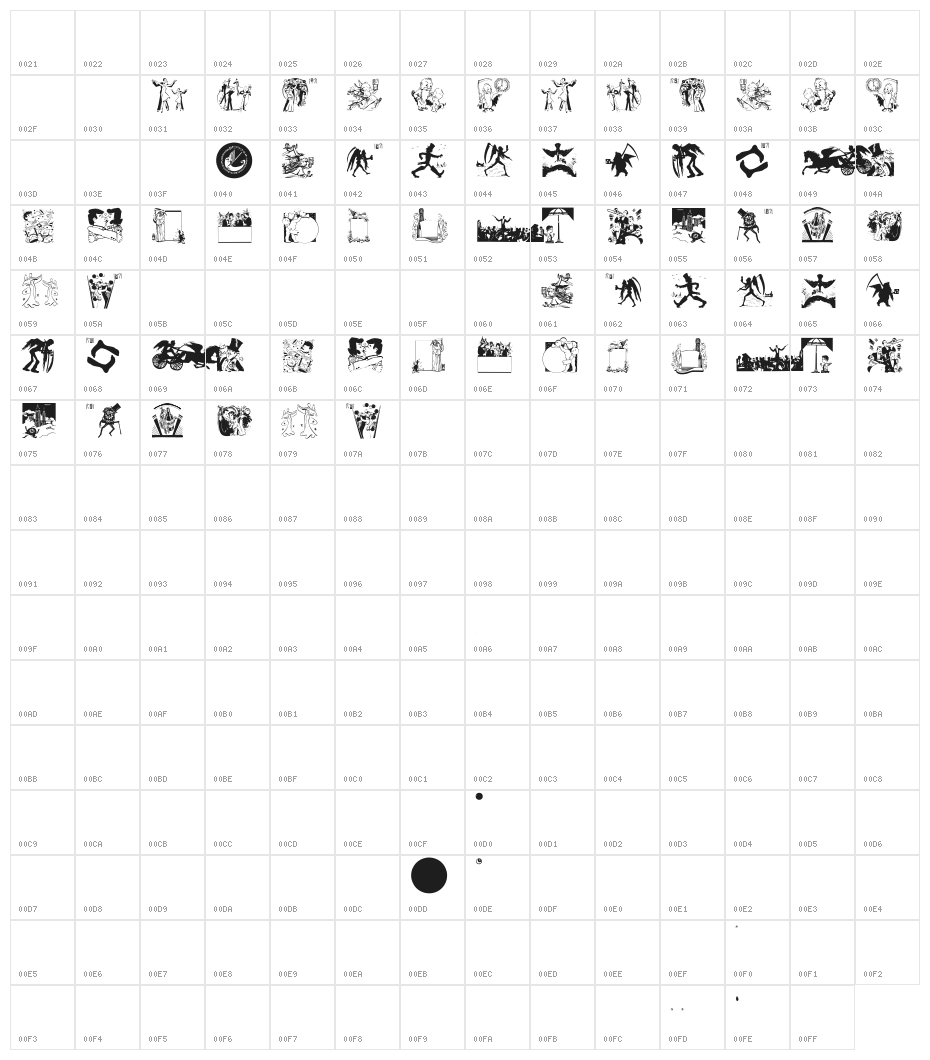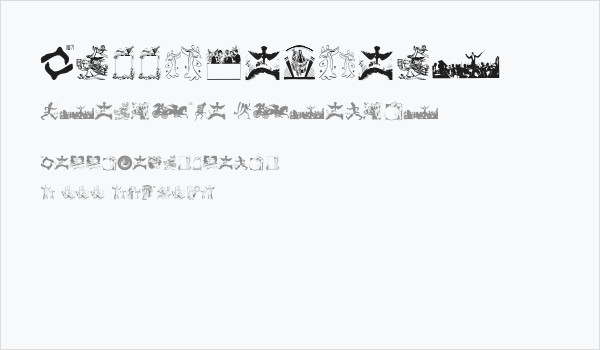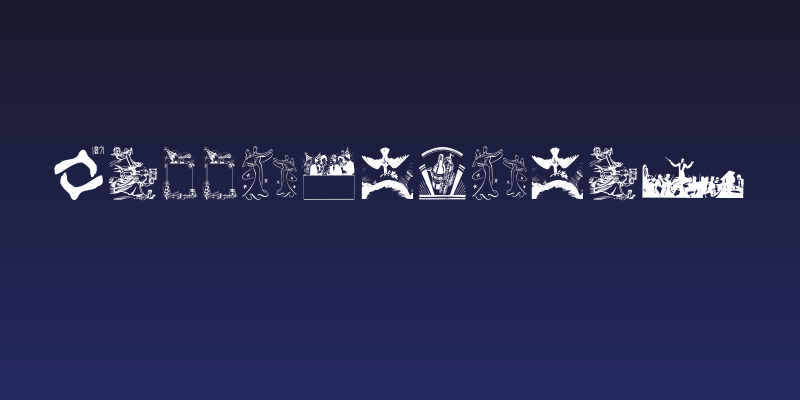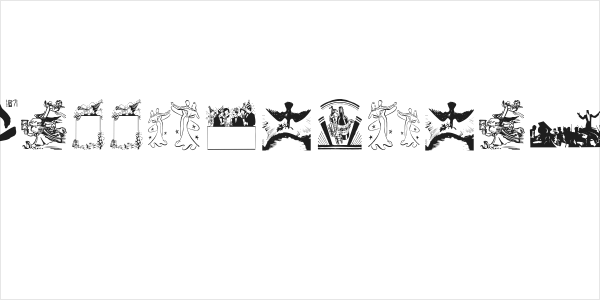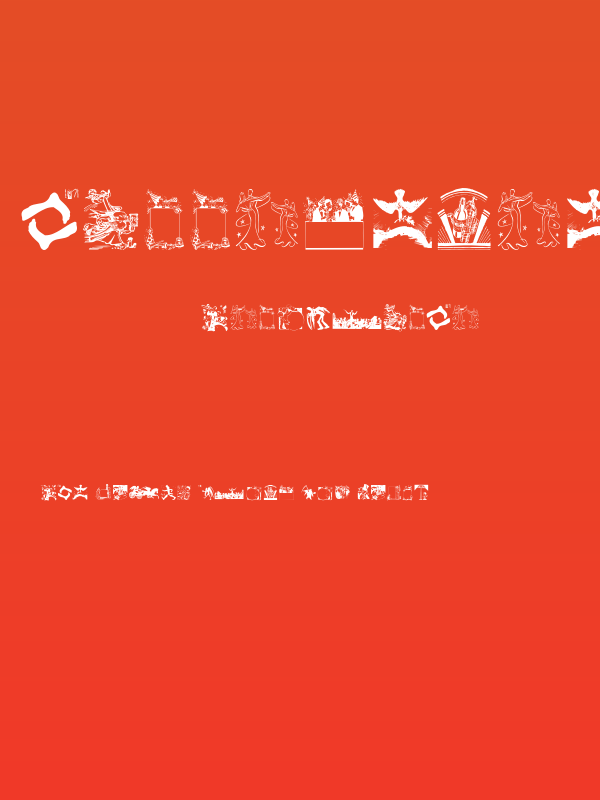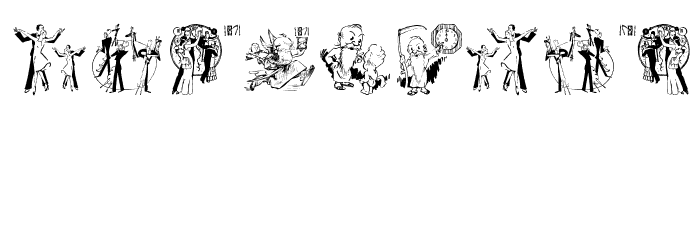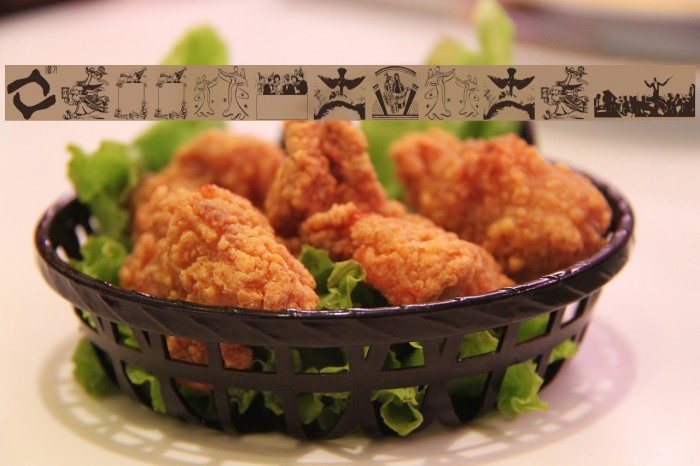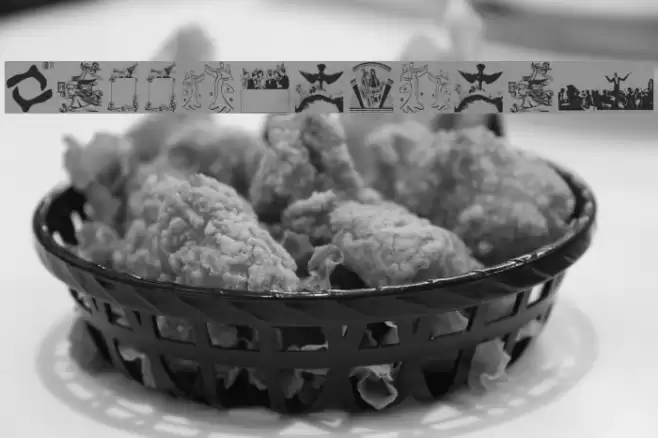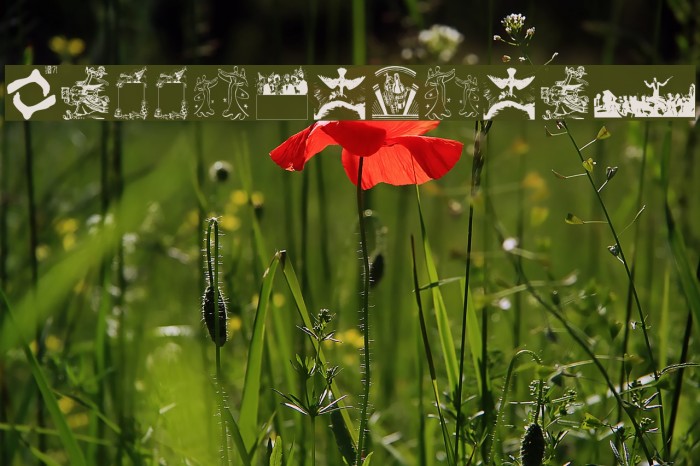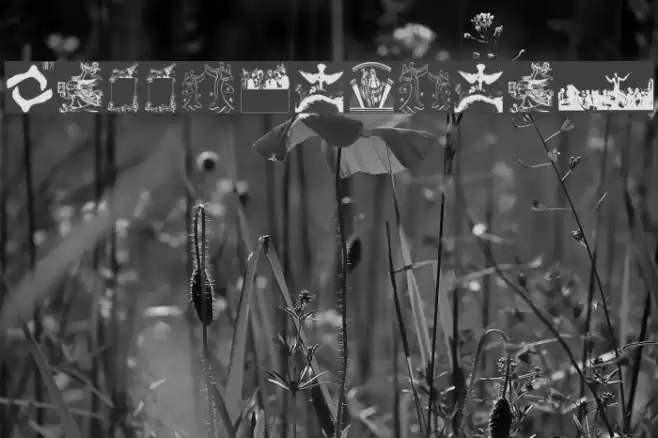
HappyNewYear Font
| Caz de utilizare | Logos, Headlines, Artistic projects |
| Proiecte propuse | Ideal for party invitations, festive banners, artistic posters, and creative event promotions. |